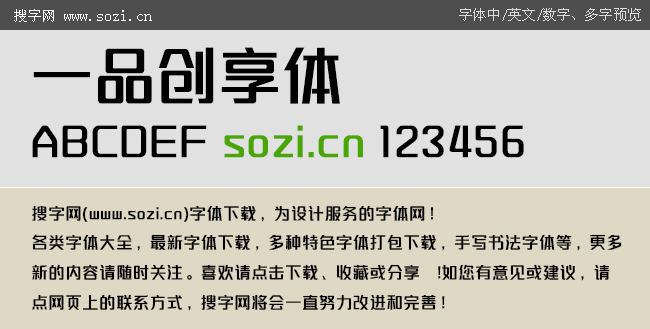
一品創(chuàng)享體
搜字網(wǎng)給大家提供一款一品創(chuàng)享體中文字體下載,一品創(chuàng)享體是一款由吉頁字庫創(chuàng)始人孫新恒受一品威客邀請作為主創(chuàng)設(shè)計師,聯(lián)合打造的一款公益造字百人計劃的字體。字體筆畫連接處采用倒角設(shè)計,使字體更加生動,線條圓潤風(fēng)趣,又簡潔明快。適用于海報設(shè)計、包裝設(shè)計、廣告設(shè)計等場景。